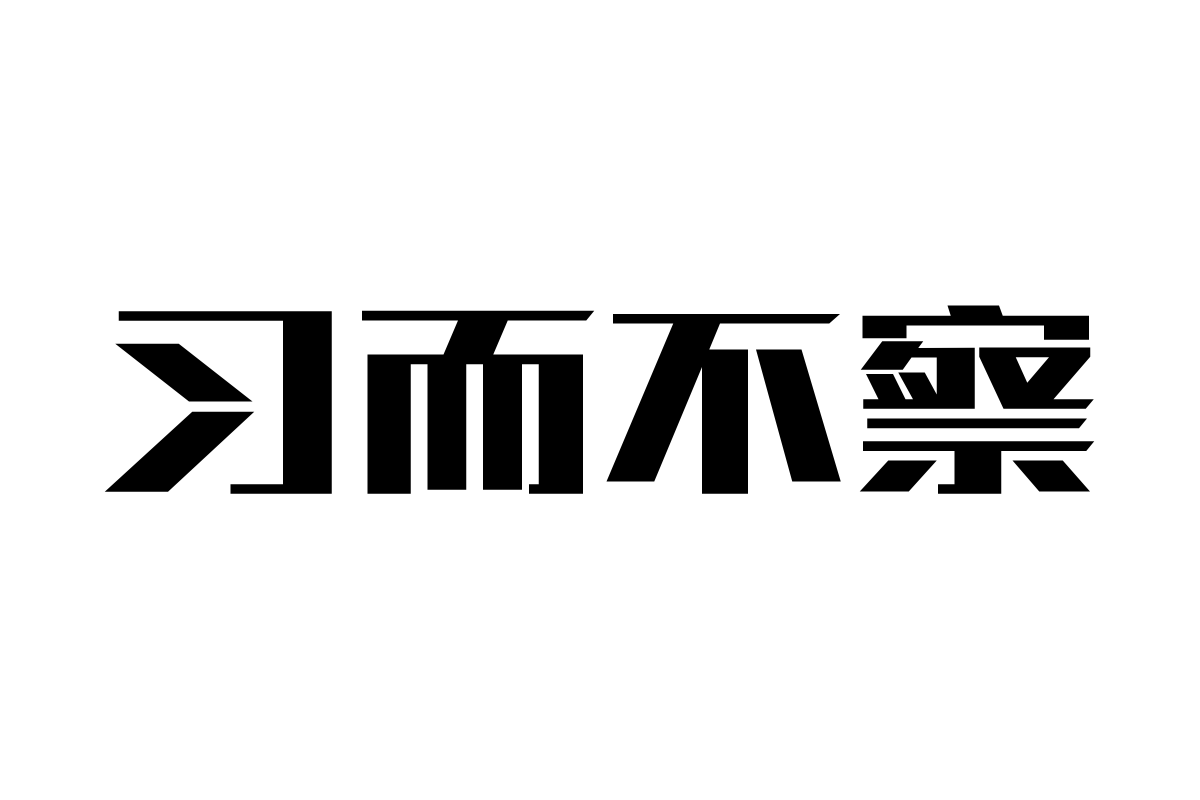
汉仪菱心体摩登版Y H1W是一款现代感十足的中文字体,具有独特的设计特点和风格。这款字体采用了简洁的线条和形状,给人一种时尚、前卫的感觉。它的笔画流畅,结构紧凑,适合用于各种需要展示现代感和创意设计的场合。
汉仪菱心体摩登版Y H1W的特点如下:
1. 简洁的线条和形状:这款字体的笔画简洁明了,线条流畅,形状独特,给人一种时尚、前卫的感觉。
2. 结构紧凑:汉仪菱心体摩登版Y H1W的字体结构紧凑,每个字符都紧密相连,使得整体看起来更加协调。
3. 易于阅读:这款字体的笔画清晰易读,适合用于需要清晰展示文字的场合,如标题、广告等。
4. 适用于多种场合:汉仪菱心体摩登版Y H1W适用于各种需要展示现代感和创意设计的场合,如网站、海报、杂志等。
总之,汉仪菱心体摩登版Y H1W是一款现代感十足的中文字体,具有独特的设计特点和风格,适合用于需要展示现代感和创意设计的场合。